Di artikel ini Computer 1001 menyajikan 10 font nuansa Indonesia: font dingbat gambar pahlawan nasional, dandanan dan rumah adat, aneka alat dan pelengkapan pramuka, font nuansa batik, serta font gaya tulisan Bali dan Jawa.
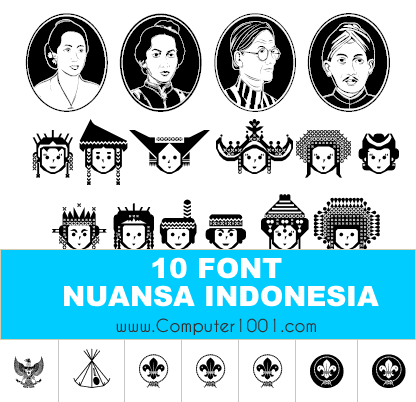
10 Font Nuansa Indonesia
- Indonesian Woman
Font dingbat wanita Indonesia dengan dandanan adat daerah. Ada 12 gambar: Jawa, Sumatera Utara, Minang Sumatera Barat, Melayu Lampung, Bali, Nusa Tenggara Timur, Jambi, Jawa Timur, Dayak Kalimantan Barat dan Timur, Karo, serta pengantin Minang.
- FTF Indonesiana Scout
Font dingbat tema pramuka Indonesia. Antara lain: aneka gambar api unggun, lambang Garuda, lambang tunas kelapa, dan lambang pramuka dunia.
- Perangko Wayang
Font dingbat gambar perangko wayang.
- Papan Kita
Font dingbat rumah adat Indonesia.
- Cermin Pahlawan
Font dingbat gambar pahlawan nasional Indonesia.
- Balinese Family
Font dengan gaya tulisan Bali.
- Jawadwipa Adisastra
Font gaya tulisan jawa gagrag Surakarta.
- Antique Paleoindonesia
Font nuansa batik.
- Batik Indo
Font dengan background motif batik.
- FTF Indonesiana Sans Javallonia
Font aksen batik.